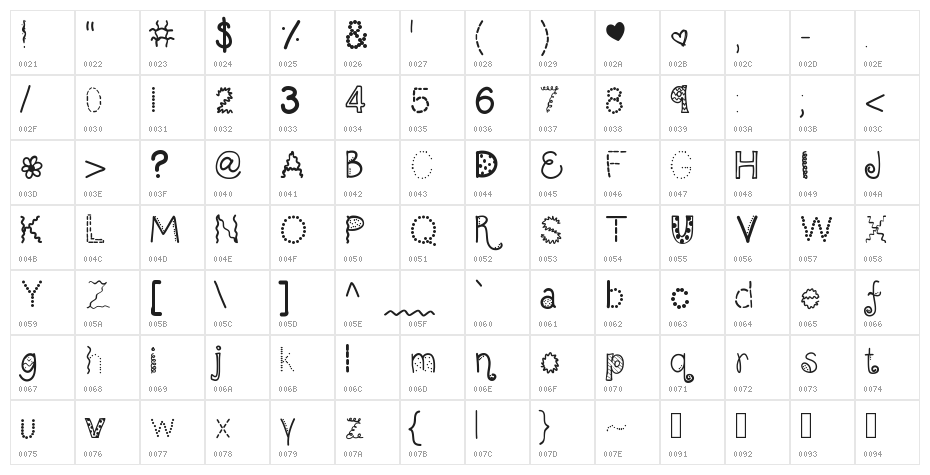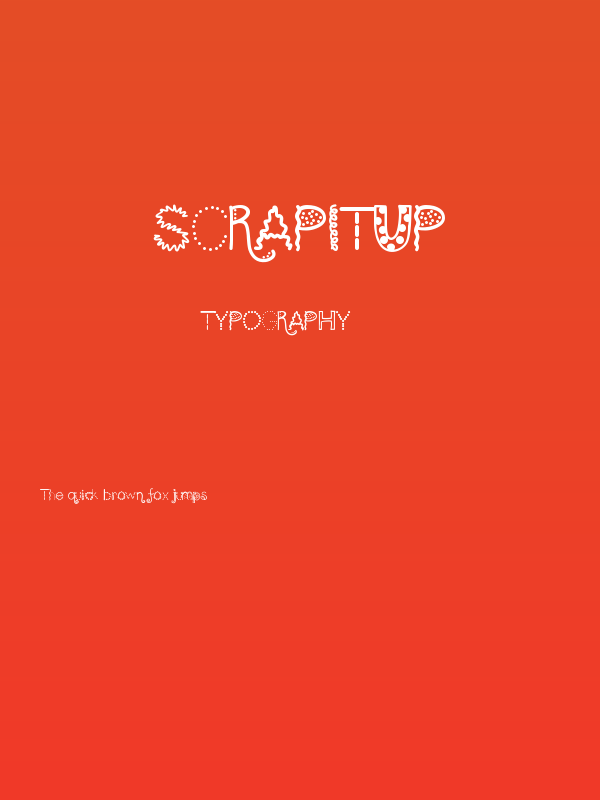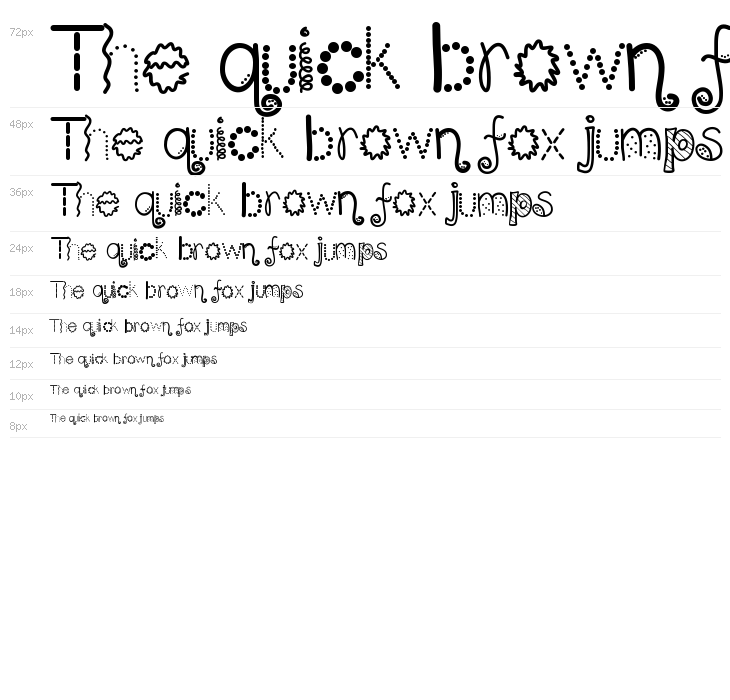
ScrapItUp Font
| Caso d'uso | Headlines, Logos, Creative projects |
| Progetti proposti | Ideal for children's books, creative posters, party invitations, and playful branding. |